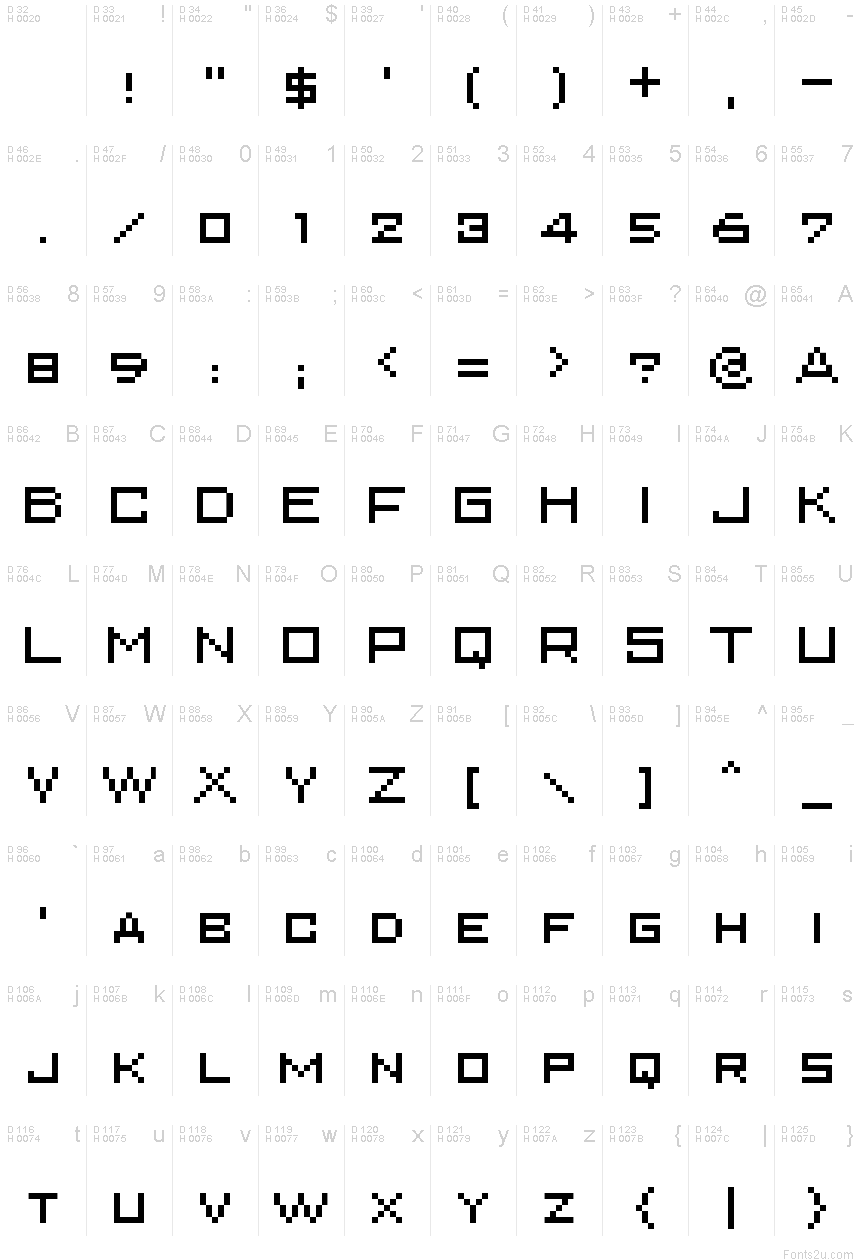
Superkarcher هو خط نقطي (Bitmap) مجاني بالحروف الكبيرة (Caps) ذو طابع ألعاب الأركيد القوي. تم بناء الحروف من كتل مربعة صلبة وزوايا قائمة حادة، مما يمنح الخط مظهراً مبسطاً يذكرنا بشاشات العرض القديمة؛ فهو يبدو خاماً، ميكانيكياً، وذا طابع مرح قليلاً.
يعمل هذا الخط بشكل طبيعي مع شعارات الألعاب، وأغلفة المجلات (Zines)، وعناوين الملصقات، وبطاقات العناوين، وتسميات الواجهات القصيرة حيث يمكن لشبكة البكسل أن تعبر عن نفسها. وباعتباره خطاً مجانياً، فإن Superkarcher مناسب أيضاً للمونوجرامات ونصوص البانر القصيرة، حيث تضمن أشكاله المدمجة والمربعة أن تبدو حتى الحروف القليلة بتصميم مدروس وبارز.